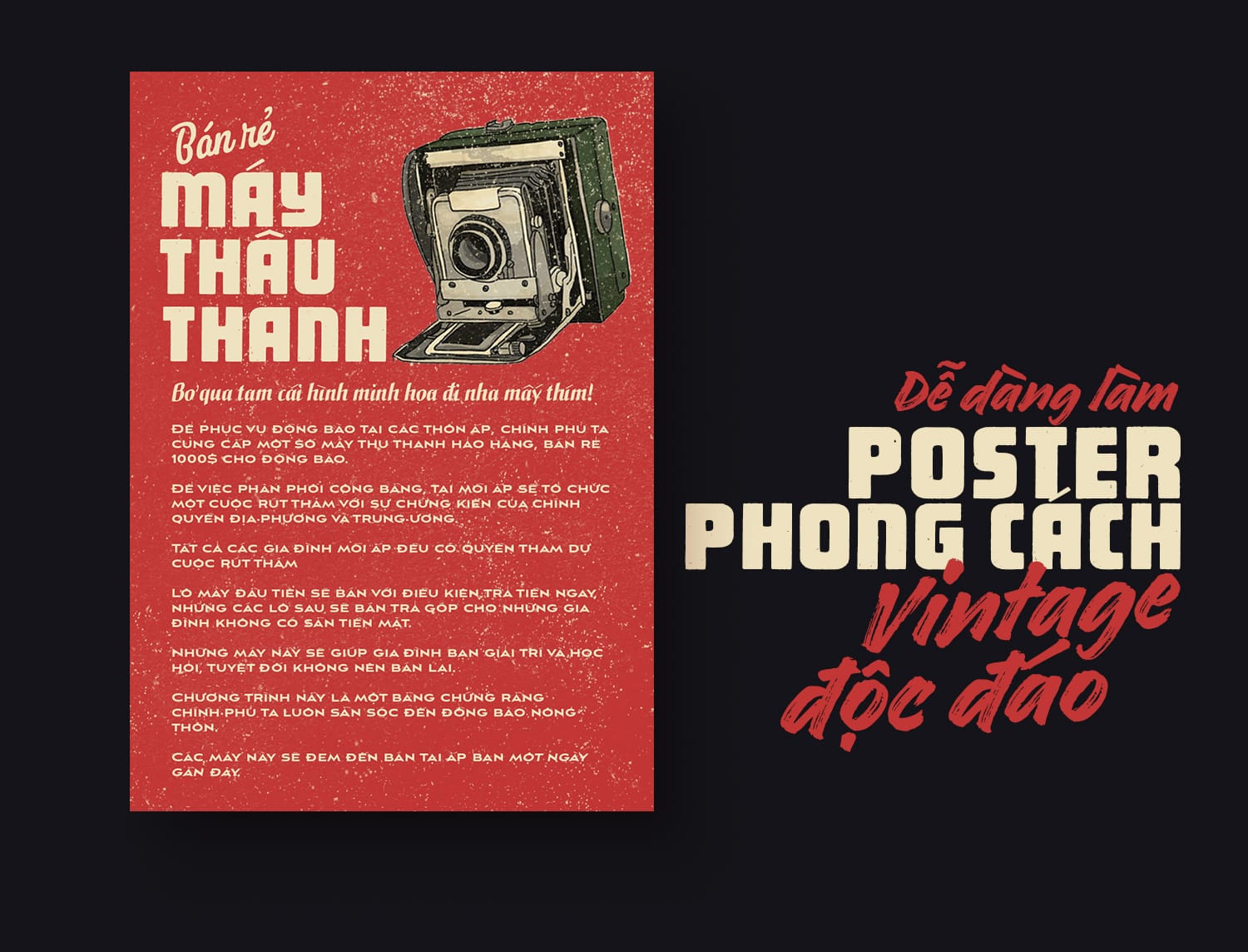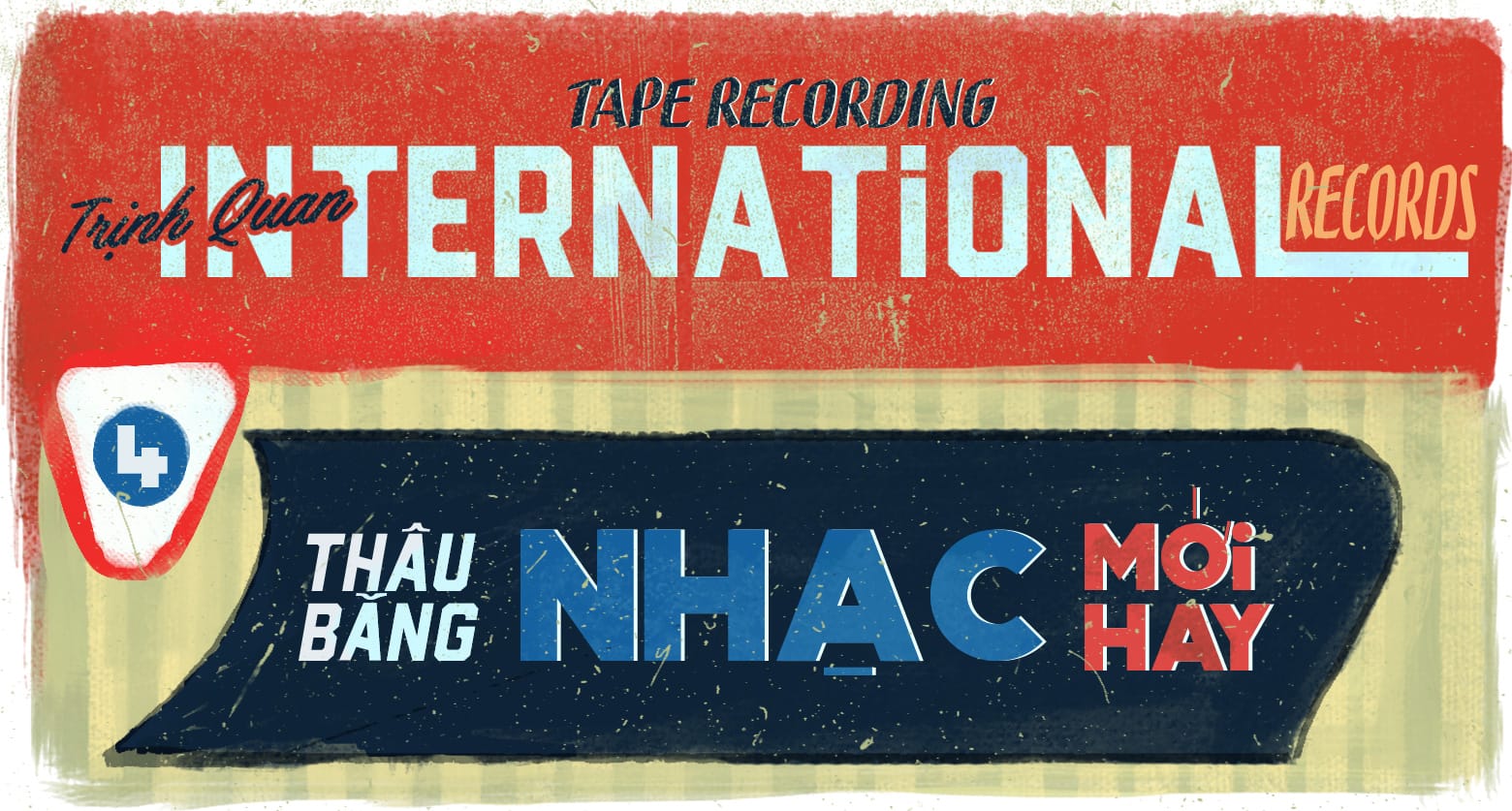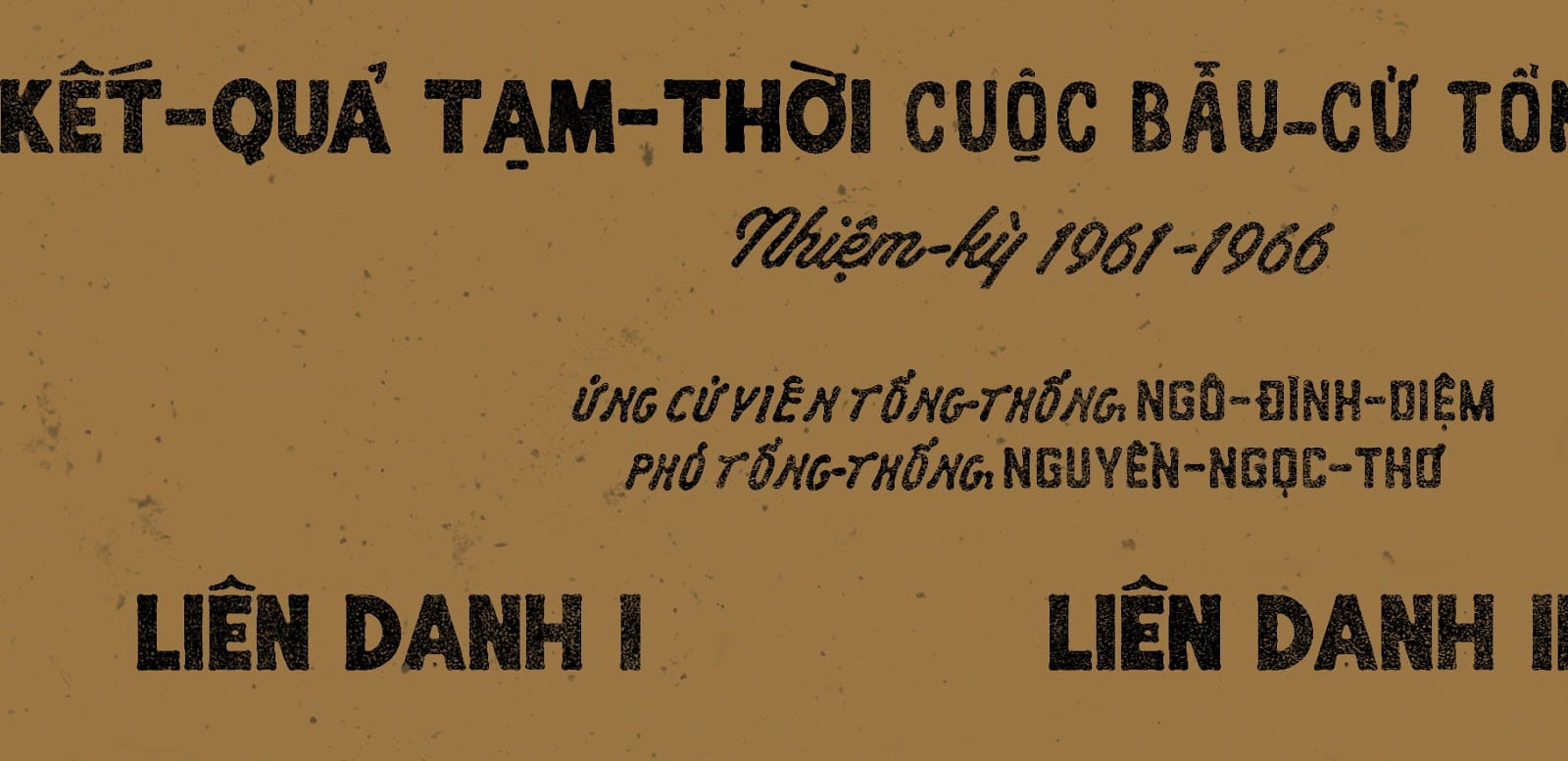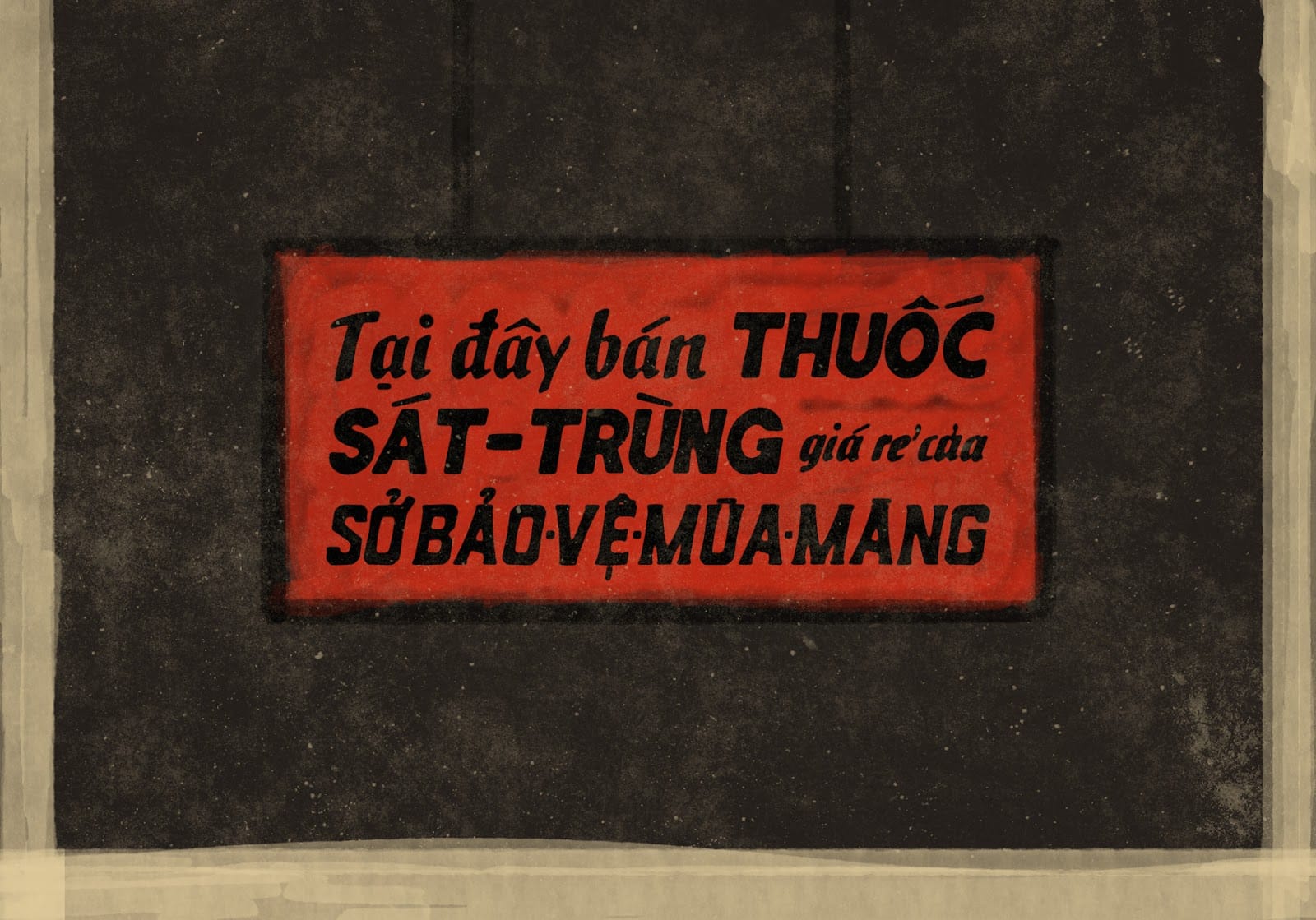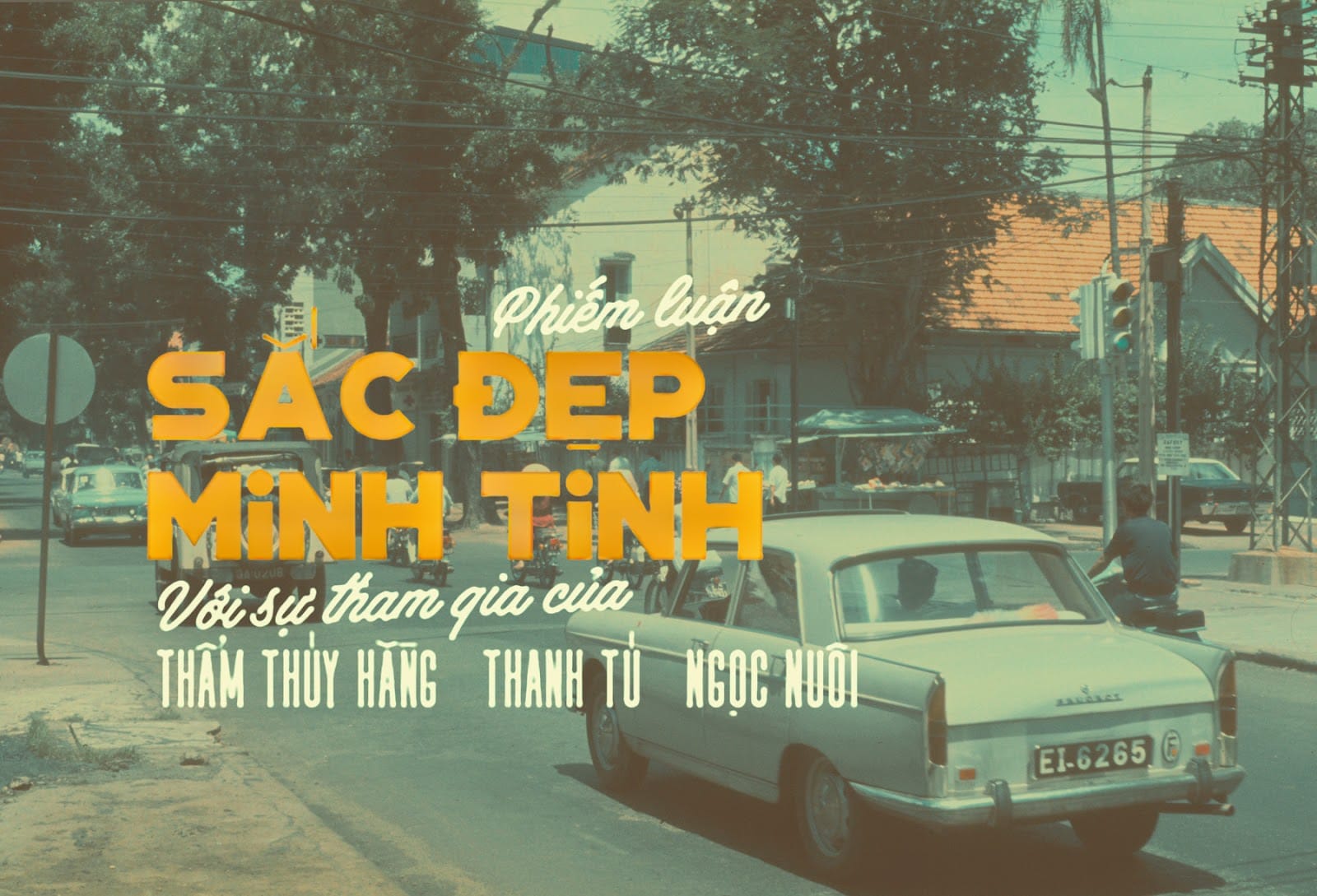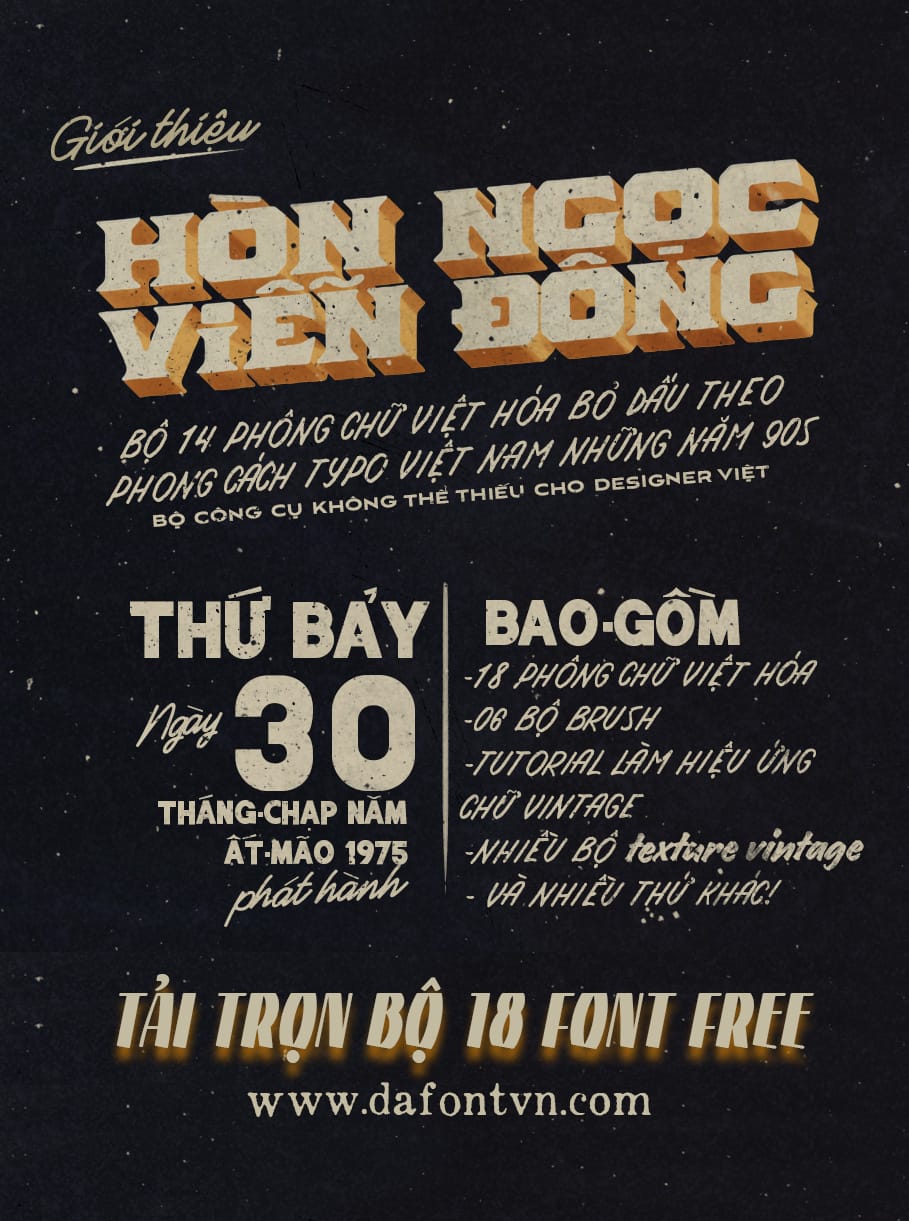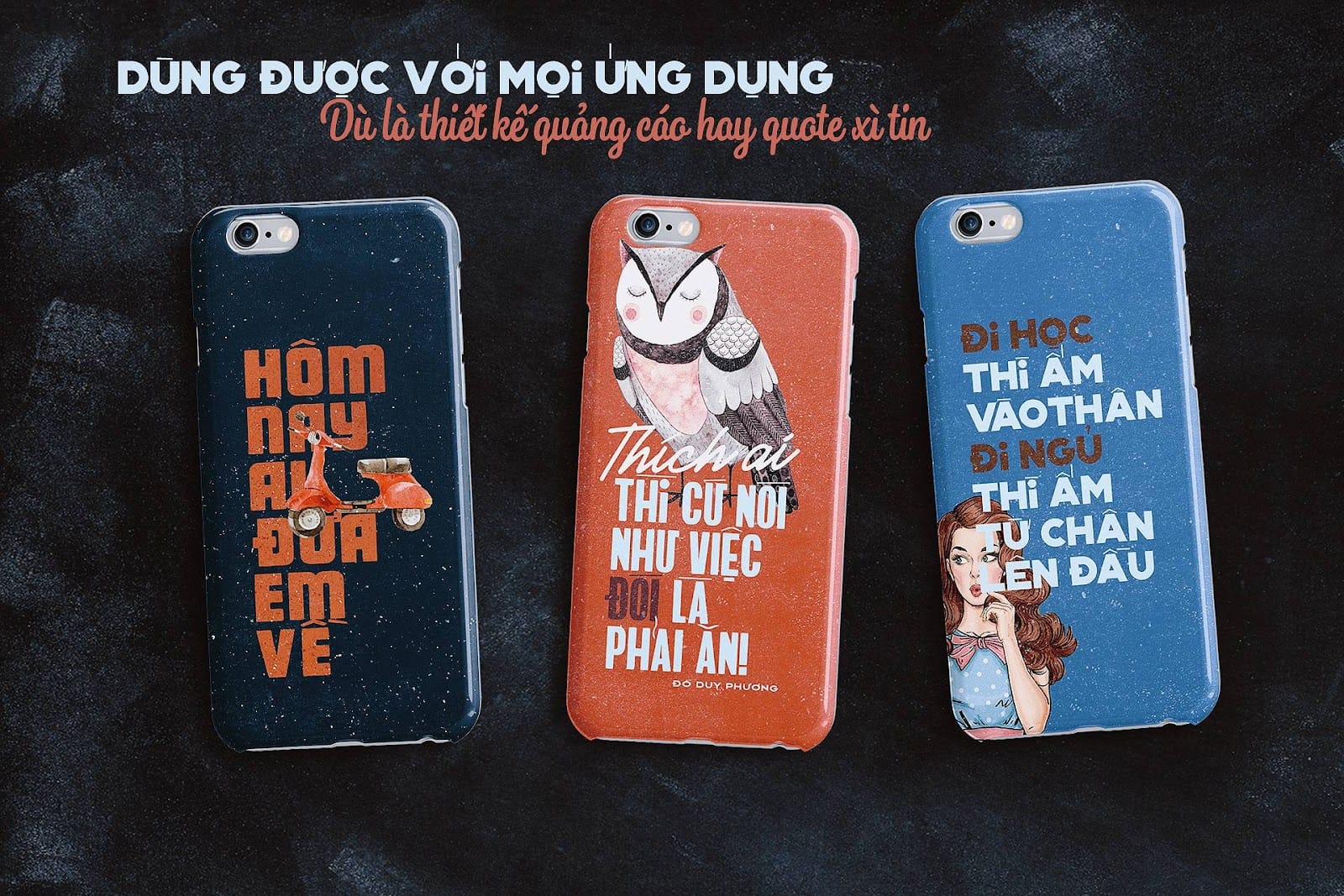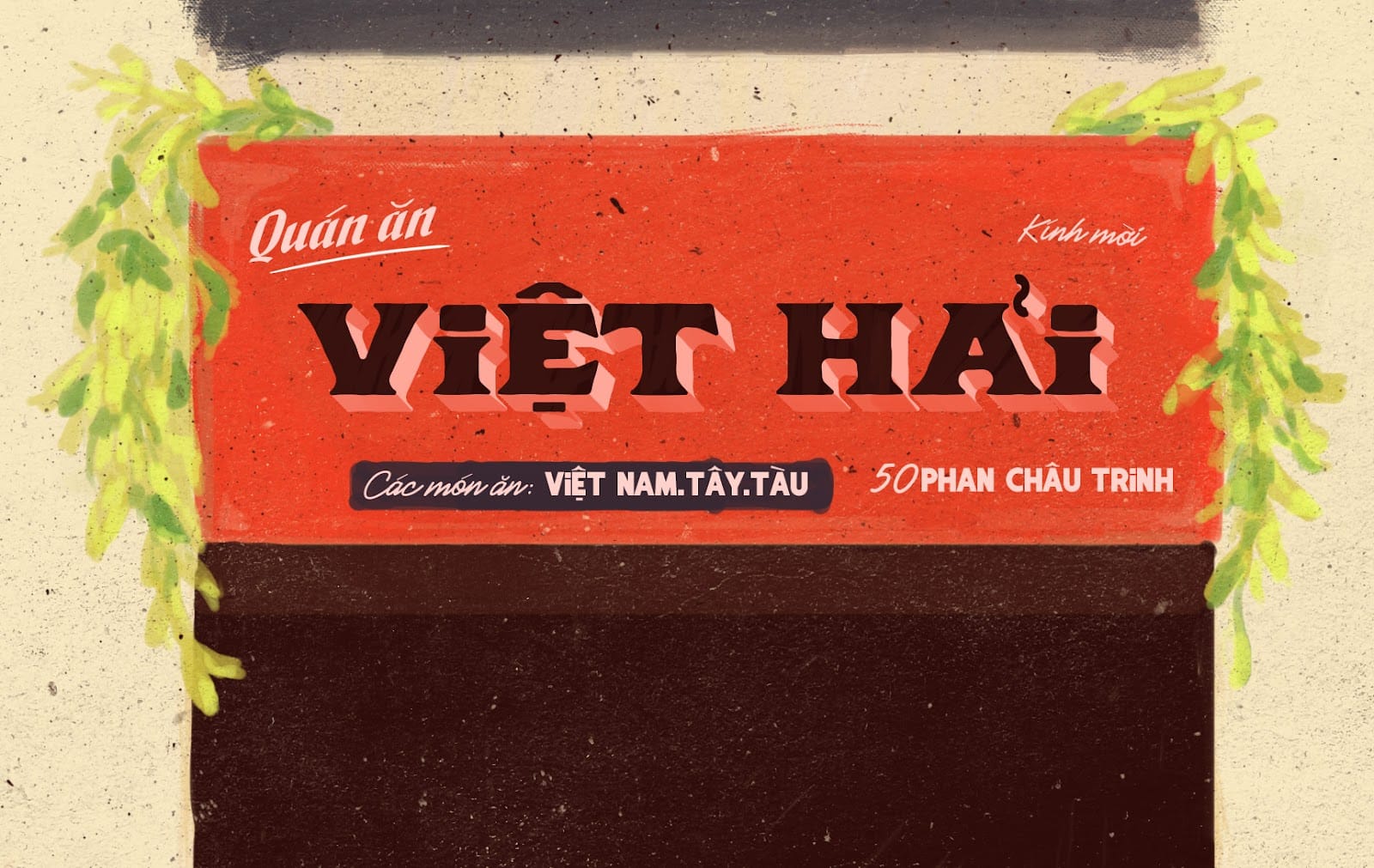
Bộ font Hòn Ngọc Viễn Đông mang phong cách xưa cũ bao gồm 18 font Việt Hóa được chọn lọc kỹ càng và rất chất lượng. Bộ font được nghiên cứu qua hàng trăm bức ảnh biển hiệu Sài Gòn Xưa, các font đều được chỉnh sửa lại để cho giống với font xưa hơn với các nét dấu mang phong cách viết chữ hơi kì lạ một chút của người xưa.